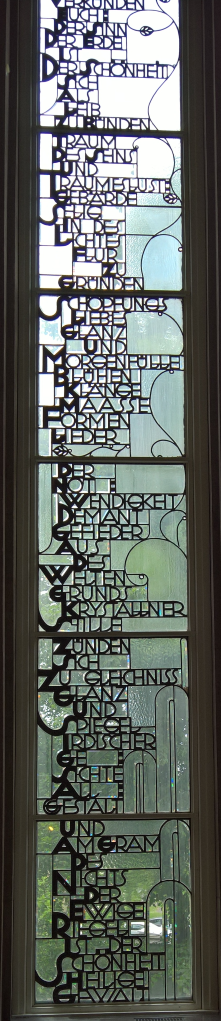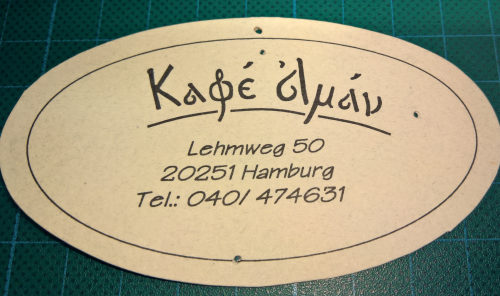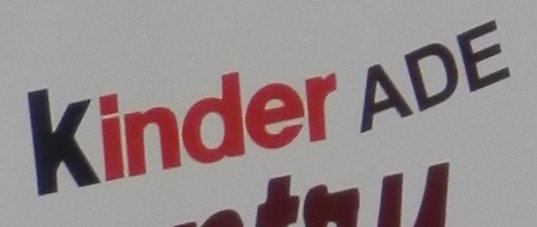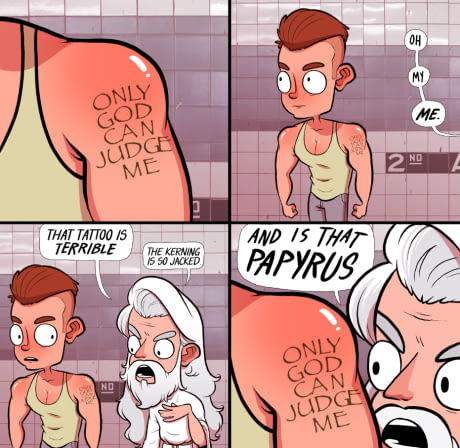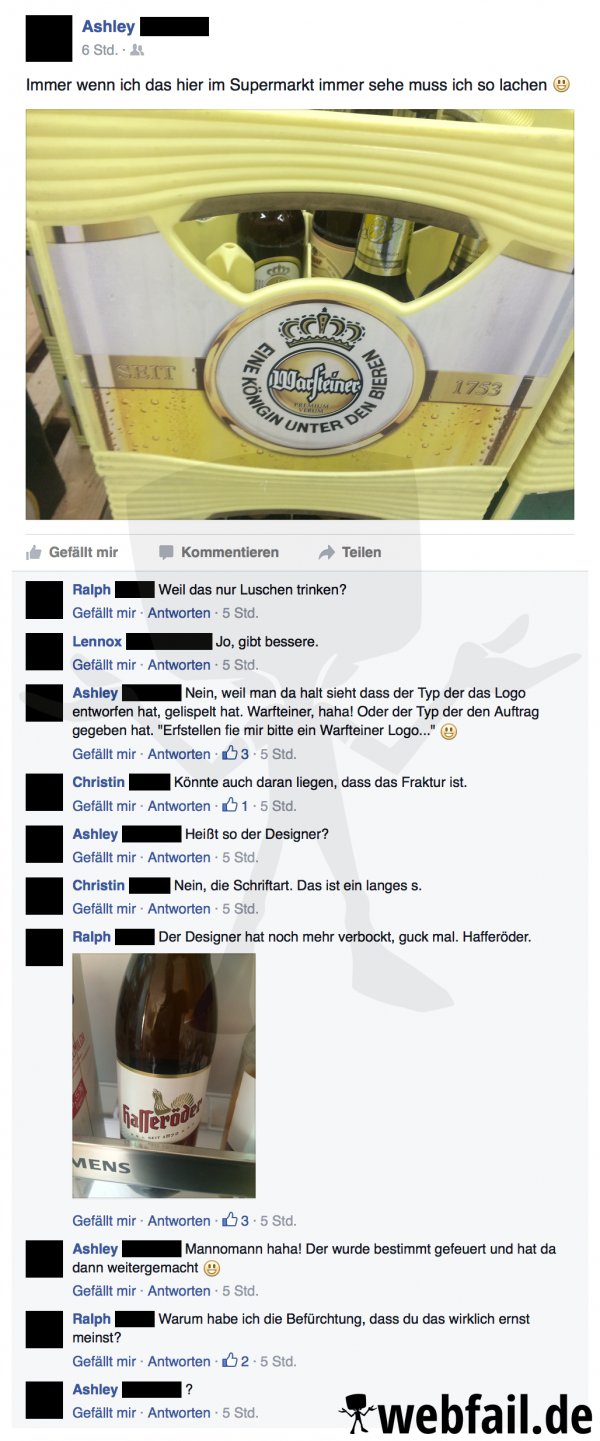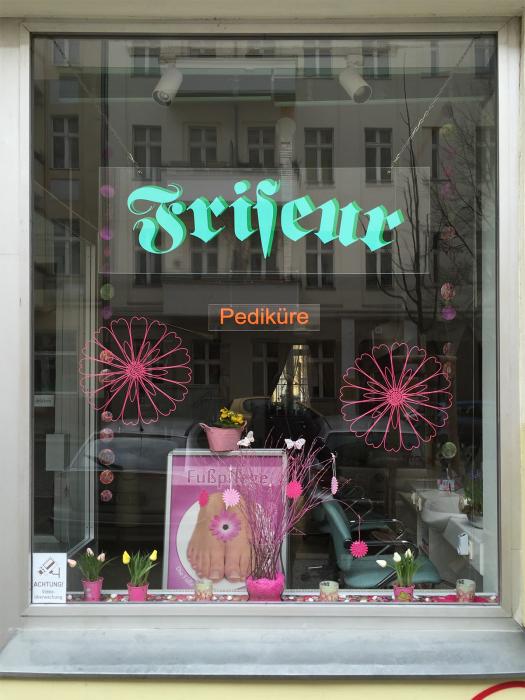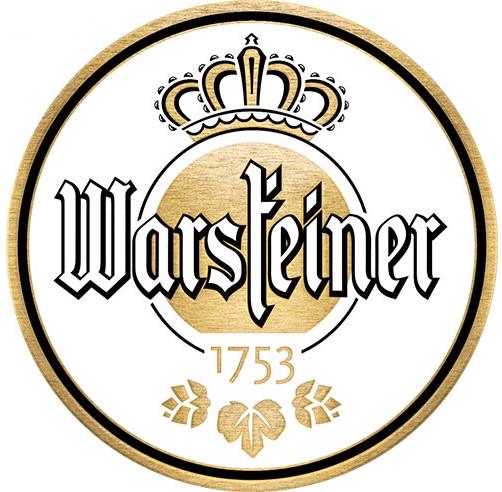
Wo ist denn da die Fuge?  :-?
Die geneigte Matrixa meint, es sprächen viele Anzeigen dafür, dass in der Fuge an eigener Matrix ein z in den Bach entfleuchte ... *flöt* ;-)
WKinder ade! Scheiden tut weh.
Aber dein Scheiden macht,
Daß mir das Herze lacht?
Hmmmm ...
Und darum haben die das Logo geändert, und damit man nicht nach dem Designer fragt, haben sie es drauf geschrieben, denn ganz bestimmt war's keiner:
Danke, xkcd ist immer gut! Zu den Unicode-Schlangen: tja, wenn wir nur Arabisch schrieben!
الـــــــــــــــعــــــــــــربـــــــــــــيــــــــــة
Kashida ist da schon fein, aber die bringen an Wortschlangen noch mehr, durch mögliche Formvarianten von Buchstaben:
(das untere in all seinen (über 3000) zulässigen Varianten ist immer identisch mit dem Wort in der oberen Bildschirmhälfte.)
Es geht zwar um Farben, aber als Palette für Texteditoren ist der Typographie-Bezug da:
Ich war heut in der Hochschule für Bildende Kunst, Ihr wisst schon, die Futura, und möchte Euch nicht die Fenster in der großen Halle vorenthalten:
links
rechts
Heute sehr gelacht in Mildstedt/Husum:
(Wobei die süddeutschen Kollegen den Lapsus vielleicht einen Hauch schneller erfassen …)